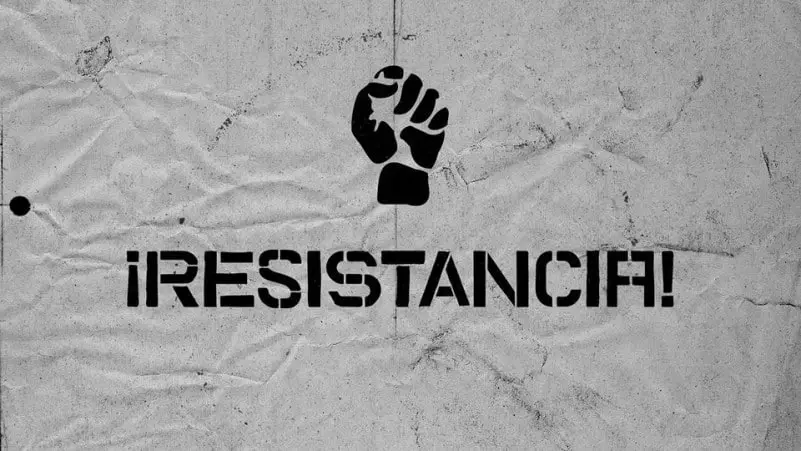
A Refuse Display Font é uma fonte display moderna que transmite uma sensação esportiva e aventurosa. Ideal para enriquecer design único com sua capacidade única de destacar texto em capas altas, a fonte reflete as desafios e contradições do nosso tempo. Rafael Nascimento, o designer responsável por essa criação, criou a fonte como um recurso inspirado nas lutas e perdas que vivemos atualmente. A Refuse Display é ideal para ser usada em stencil de grande tamanho – preferencialmente como uma ferramenta de resistência. O autor menciona que a tipografia tem o poder constante de propor formas novas de reflexão, distribuição e acesso. Esta fonte oferece outra arma na batalha contra os desafios atuais. Composta em letras maiúsculas sólidas, essa fonte moderna é perfeita para quem deseja dar vida às vozes silenciadas e opressas, proporcionando uma nova plataforma de expressão.